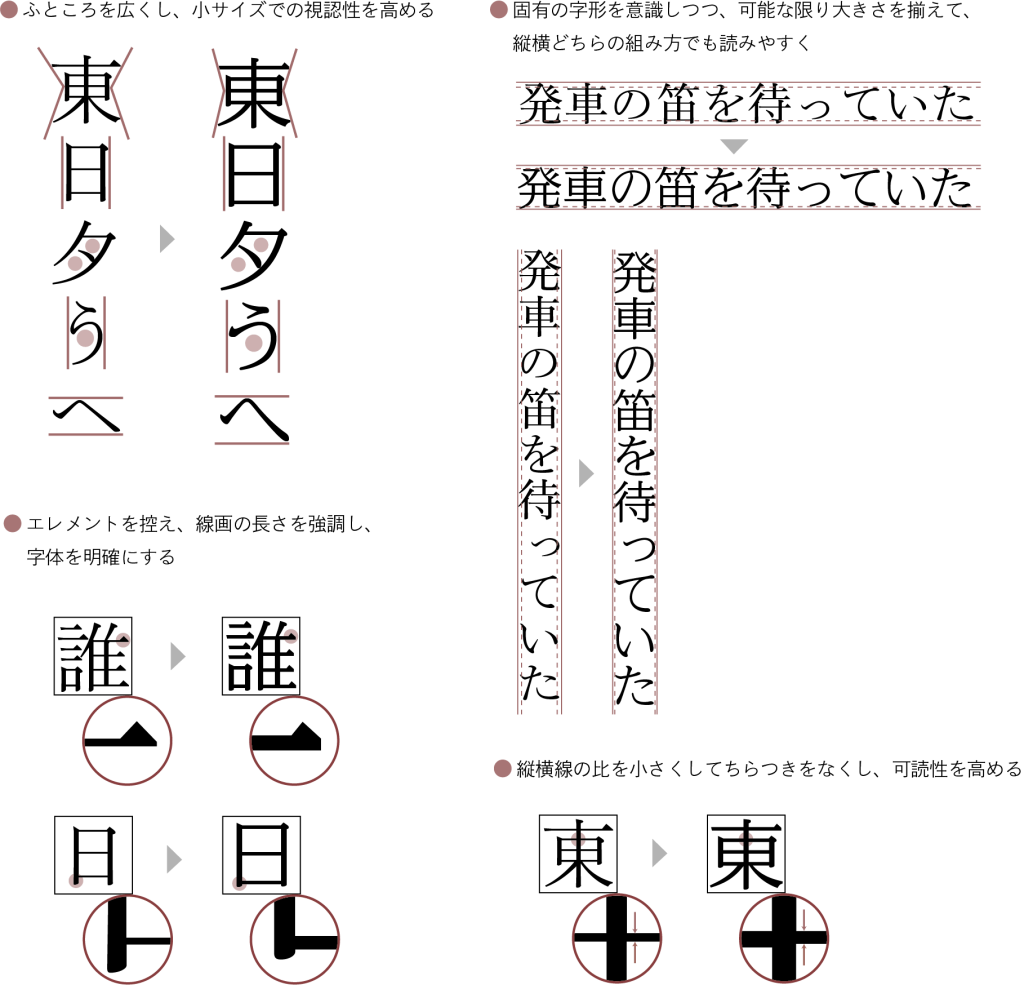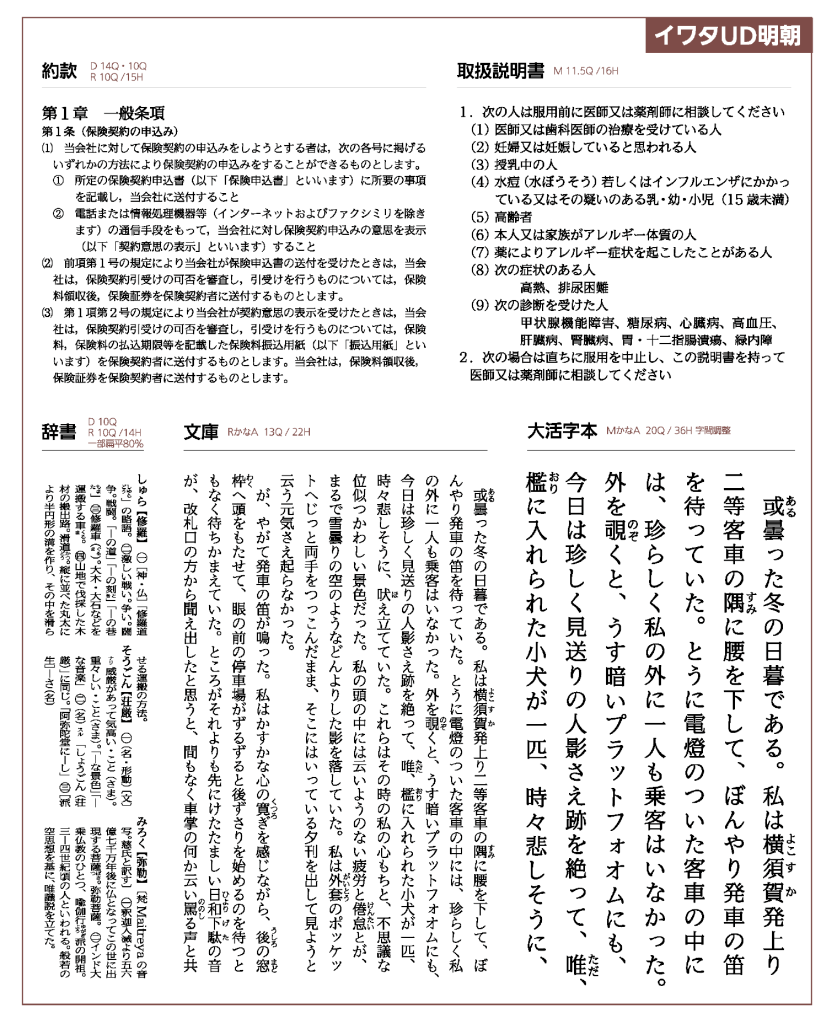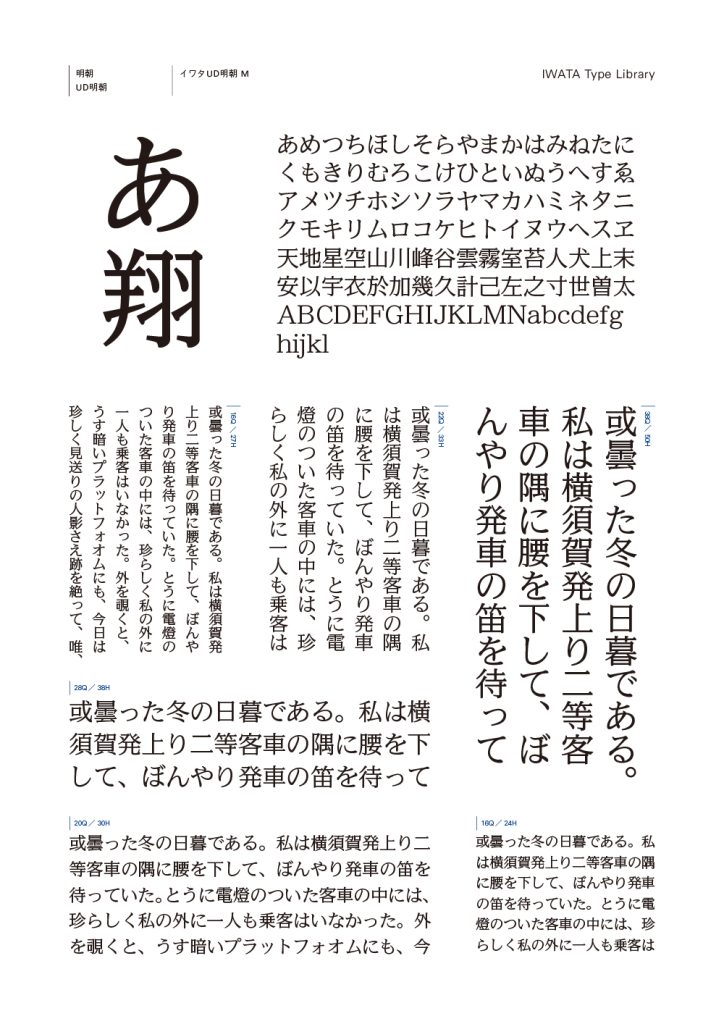
すべてのひとに見やすい、読みやすいフォントを目的に、日本で最初にユニバーサルデザイン(UD)視点で開発された明朝体です。一般的な明朝体に比べ横線が太く、大きく揃った字面設計により実現した高い視認性により、画面表示でのちらつきが少なく、縦組み・横組みのどちらでもラインが揃うバランスの良い組版が可能です。仮名のバリエーションは表情豊かな「かなA」~「かなD」の4 種類を揃え、用途に応じて使い分けることで表現の幅が広がります。ユニバーサルデザイン(UD)の視点を取り入れ、見やすさと読みやすさを追求した明朝体です。横線を太めにし、字面を大きくすることで視認性を向上させ、ちらつきを抑えた目に優しいデザインが特徴です。
書体デザインのポイント
誤読を防ぎ読みやすさを向上させるために、デザインにいくつもの工夫がされています。
※「イワタ明朝体オールド」と「イワタUD 明朝R」を比較しています
従来、明朝体では不得意とされてきた横組みの文章や、小サイズでの組版に最も威力を発揮します。また、ちらつきの少ない特徴を活かし、理路整然とした紙面を叶えます。
開発の背景
高齢化社会が進んだ現在、老眼、白内障等々、加齢による視力の低下に悩む人が急増しています。
一方で製品の多機能・高機能化、小型化、デジタル化が急速に進んでいます。 このような環境においては、文字こそUD の視点で作られたものが必要と考え、誰にとっても読みやすい文字、「イワタUD フォント」を開発するに至りました。
一般的な書体での読みやすさ、見やすさの課題